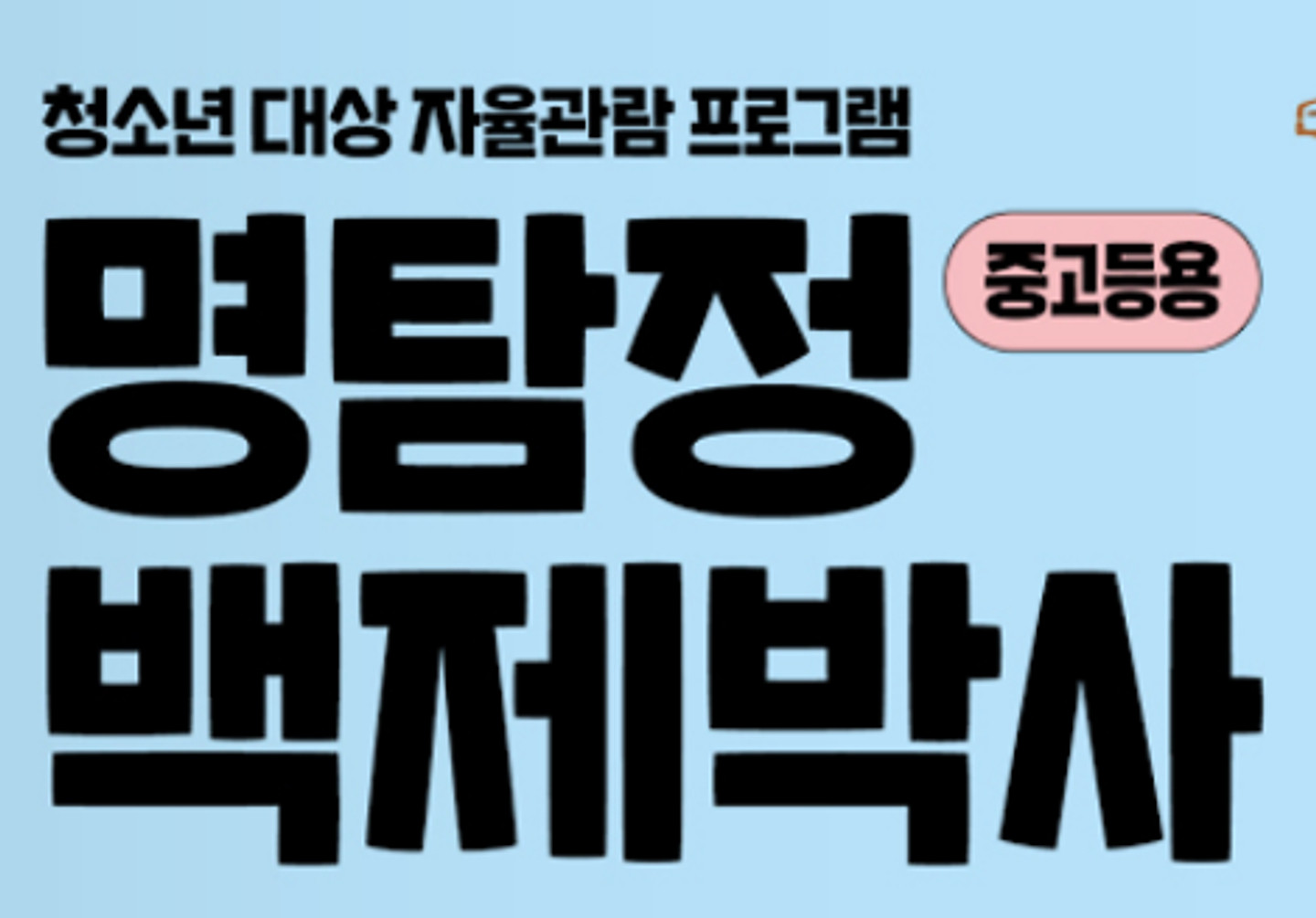
이 폰트 뭔가유??
이 폰트 뭔가용?
이 펀트 뭔가요..? ㅜㅜ
와.. 이 예쁜 폰트 뭔가요?
무슨 글씨체일까요? 이서윤체는 아닌 것 같습니다ㅠㅠ
여기 사용된 폰트명이 궁금해요 ㅜㅜ 미리캔버스에서 사용한 폰트입니다.
이거 무슨 폰트인지 알려주세요!
이 폰트 무엇일까요???
이거 무슨 폰트일까여 ㅜㅜ
라인 끝쪽에 한쪽은 라운드고 한쪽은 뾰족하네요.
폰트 두개 다 궁금해요ㅠㅠㅠ